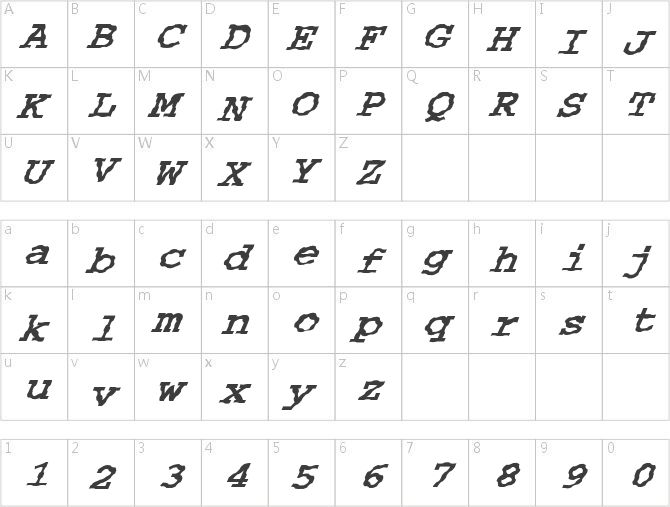
FZ DIGITAL 3 WAVEY ITALIC
FZ DIGITAL 3 WAVEY ITALIC介紹
FZ DIGITAL 3 WAVEY ITALIC字體字庫是一款讓人賞心悅目、百看不厭的英文字體,適合各類廣告和產品包裝設計應用,字體大小0.08MB,格式為ttf字體,上傳用戶是蕪耆蕪,作者/版權方為未知